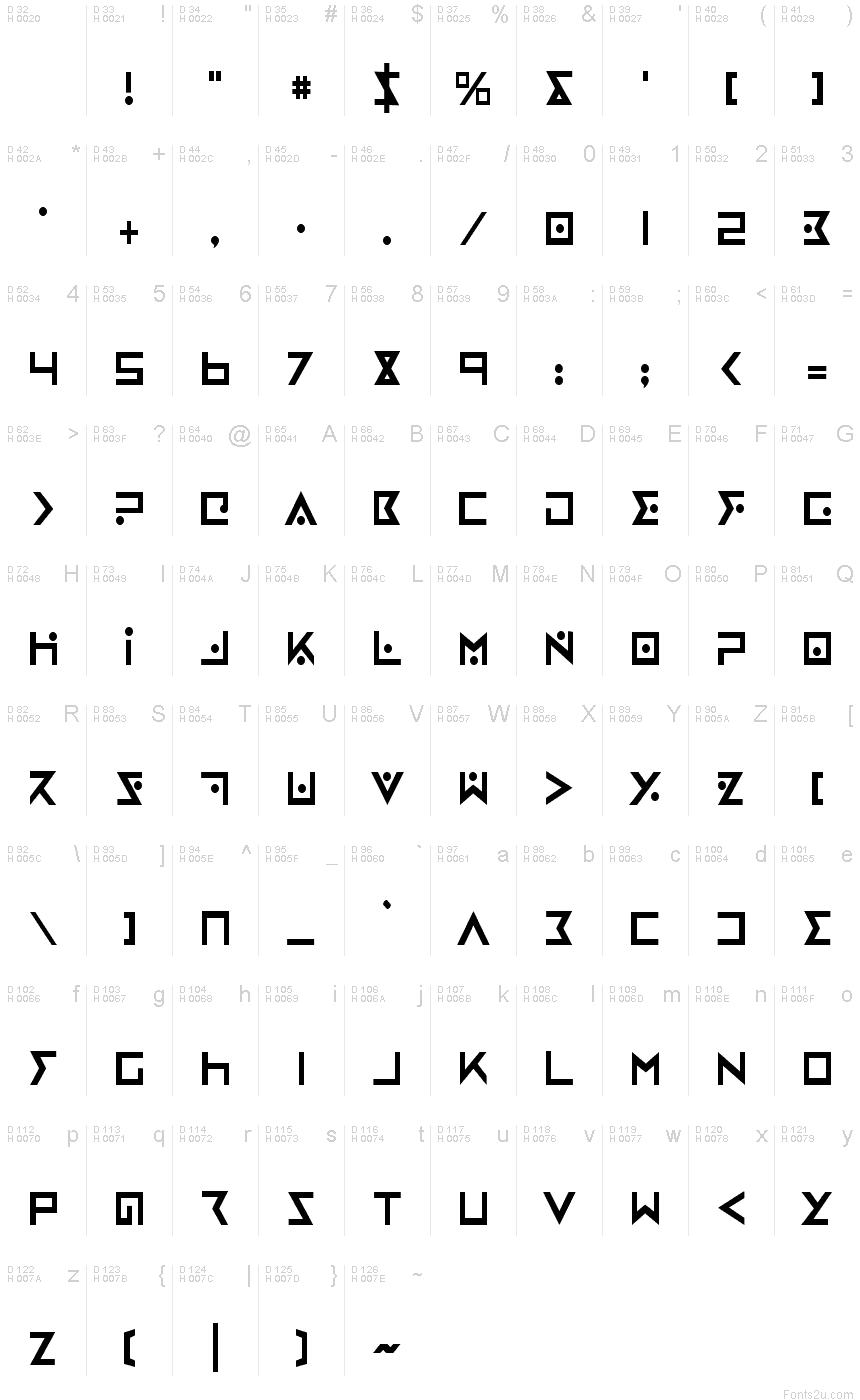
Iron Cobra Condensed, stworzony przez Iconian Fonts, to bezpłatny, techniczny krój pisma typu "caps", charakteryzujący się kanciastym, futurystycznym stylem. Wąskie litery, kwadratowe krzywe i ostro cięte przekątne tworzą zwartą strukturę, która sprawia wrażenie zaprojektowanej technicznie, a nie zdobniczej.
Świetnie sprawdzi się w logotypach gier, brandingu e-sportowym, plakatach science-fiction, okładkach albumów elektronicznych, grafice interfejsów i filmowych napisach tytułowych. Ten darmowy font doskonale nadaje się do krótkich nagłówków i haseł, gdzie wąskie proporcje oszczędzają miejsce, a wyraziste geometryczne cięcia nadają projektowi charakteru.
Iron Cobra Condensed